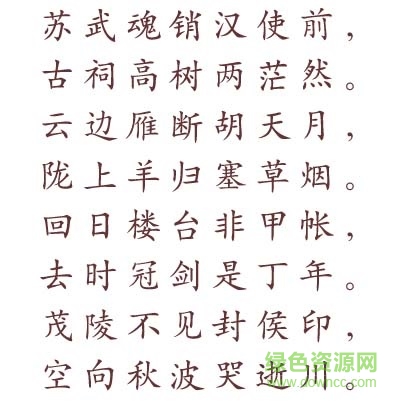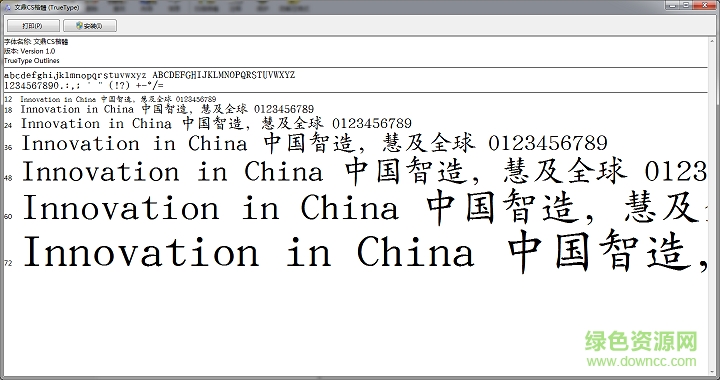
文鼎cs楷體字體是一款方正端莊的楷體字體,在課本、書本上應(yīng)該比較常見,其他地方也經(jīng)常用到?,F(xiàn)在綠色資源網(wǎng)小編為大家?guī)砦亩s楷體ttf免費版,有需要的用戶趕快來下載體驗吧!
楷書也叫正楷、真書、正書。從程邈創(chuàng)立的隸書逐漸演變而來,更趨簡化,橫平豎直。《辭?!方忉屨f它“形體方正,筆畫平直,可作楷模?!惫拭瑫?。始于漢末,通行至現(xiàn)代,長盛不衰。
楷書的產(chǎn)生,緊扣漢隸的規(guī)矩法度,而追求形體美的進一步發(fā)展,漢末、三國時期,漢字的書寫逐漸變波、磔而為撇、捺、且有了“側(cè)”(點)、“掠”(長撇)、“啄”(短撇)、“提”(直 鉤)等筆畫,使結(jié)構(gòu)上更趨嚴(yán)整。如《武威醫(yī)簡》、《居延漢簡》等??瑫奶攸c在于規(guī)矩整齊,是字體中的楷模,所以稱為楷書,一直沿用至現(xiàn)代。